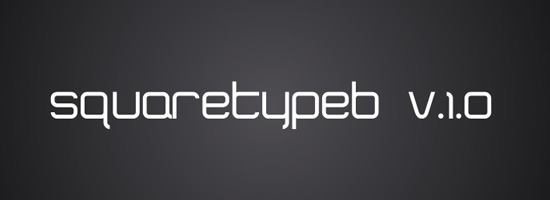
30个超个性独特字体演示及打包下载
字体对于一个设计师,尤其是平面或网页设计师来讲,是非常重要的。像M4电脑中的字库文件,已经达到近10G的容量。常用的中文字体,大概有30种,常用的英文字体,更有近100种。今天推荐给大家的这些字体,是风格比较另类的,不属于高清晰、简洁风格类型,乍一看上去,有点乱糟糟的,仔细一看,却又非常的漂亮。
1. MDRS-FD01
MDRS-FD01
2. Labrat
Labrat
3. TYPORM01 Round ans Square
TYPORM01 Round ans Square
4. SquaretypeB
squaretypeB
5. Knarf art font
Knarf art font
6. Velocity
Velocity
7. Synthetique
Synthetique
8. Amputa Bangiz Standard TTF
Amputa Bangiz Standard TTF
9. Giant Head
Giant Head
10. Snickles
Snickles
11. Times New Yorker
Times New Yorker
12. Vintage
Vintage
13. GOCA LOGOTYPE
GOCA LOGOTYPE
14. Parallello
Parallello Font
15. Karabine
Karabine
16. Infected
Infected
17. Facet
Facet
18. Drift Type
Drift Type
19. Multistrokes
Multistrokes
20. Cat Basah Kental!!!
Cat Basah Kental!!!
21. Que FONTita
Que FONTita
22. Confessions
Confessions
23. Madredeus
Madredeus
24. Vtks Revolt
Vtks Revolt
25. Exus Pilot
Exus Pilot
26. VAL
VAL
27. Outlaw
Outlaw
28. Kilogram
Kilogram
29. Ballpark
Ballpark
30. Orial
Orial